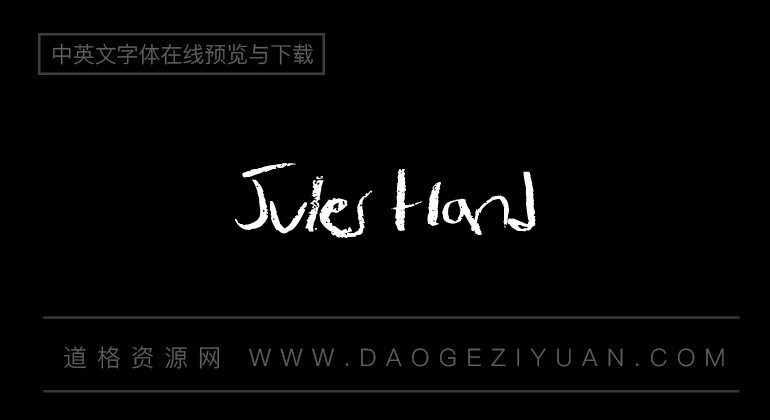
Jules Hand
Jules Hand 是一款由 Handmadefont 公司设计的字体,它具有细节丰富的手写曲线,结合现代感的笔画,极具个性的外观,适用于各类品牌设计、标识设计、海报设计、网页设计等。Jules Hand 拥有丰富的字体组合,可以满足不同设计需求,比如拥有多种字重、字宽、字高、字间距等,以及丰富的标点符号、数字和特殊符号,可以满足不同的设计要求。
Jules Hand是一款非常不错的手写艺术字体,具有很好的视觉感,适合于文化类的宣传设计、商业类品牌的广告和产品包装设计以及个性化文字排版等较多场景。